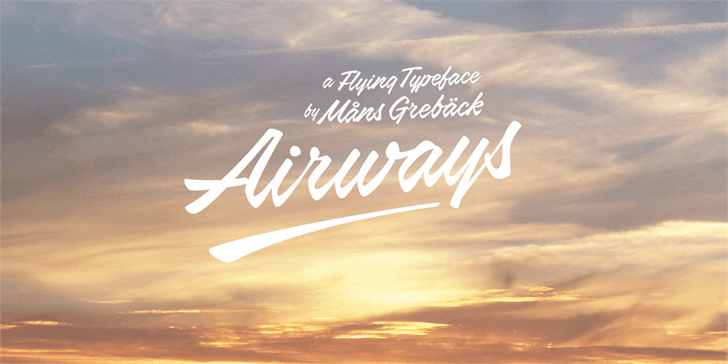
Airways Font – Download Grátis
A Airways Font é uma elegante cesta de escrita a mão criada pelo designer Hamilton, perfeita para um toque pessoal em seu design visual. Seu traço suave e delicado oferece aos designers uma maneira suave de adicionar um elemento humano às suas criações digitais. Com uma ampla gama de usos potenciais, desde pequenos detalhes que chamam atenção até grandes elementos em layouts de sites ou revistas, essa fonte manuscrita Hamilton proporcionará seu projeto um toque único e autêntico. Para quem está pronto para incorporar esse charme na sua próxima criação, visite o site oficial do designer para adquirir uma licença comercial. Esta é mais do que simplesmente uma fonte de escrita; ela traz vida à sua ideia ao oferecer um toque único e pessoal que ressoa com quem vê. Não importa se você está criando material online, impresso ou até mesmo conteúdo audiovisual – a Airways Font terá o seu design personalizado.